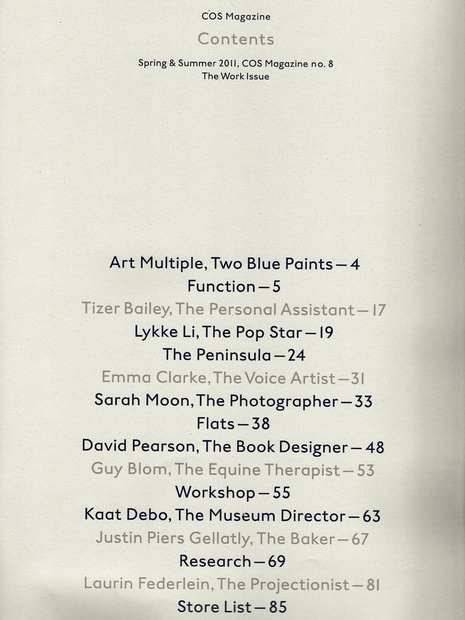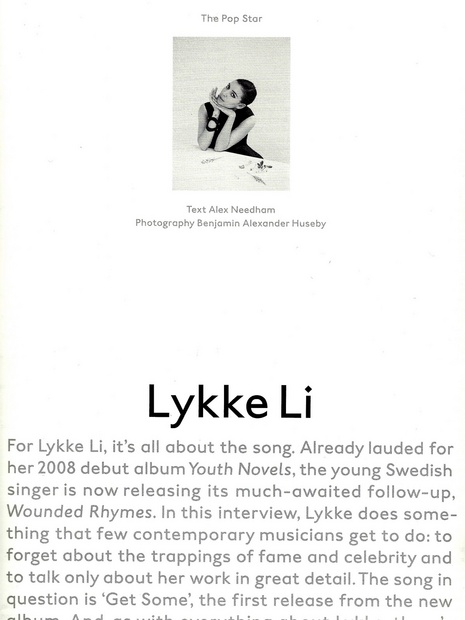
Wie heißt diese Schrift? Ähnlich ITC Johnston
Es ist weder die ITC Johnston, P22 Underground noch Granby (anderes "l", "a", "1")… Erkennt sie jemand und kann mir den Namen nennen?
Das gerade "l" ist im OS Zeichensatz der ITC Johnston vorhanden, ebenso das einstöckige a ...